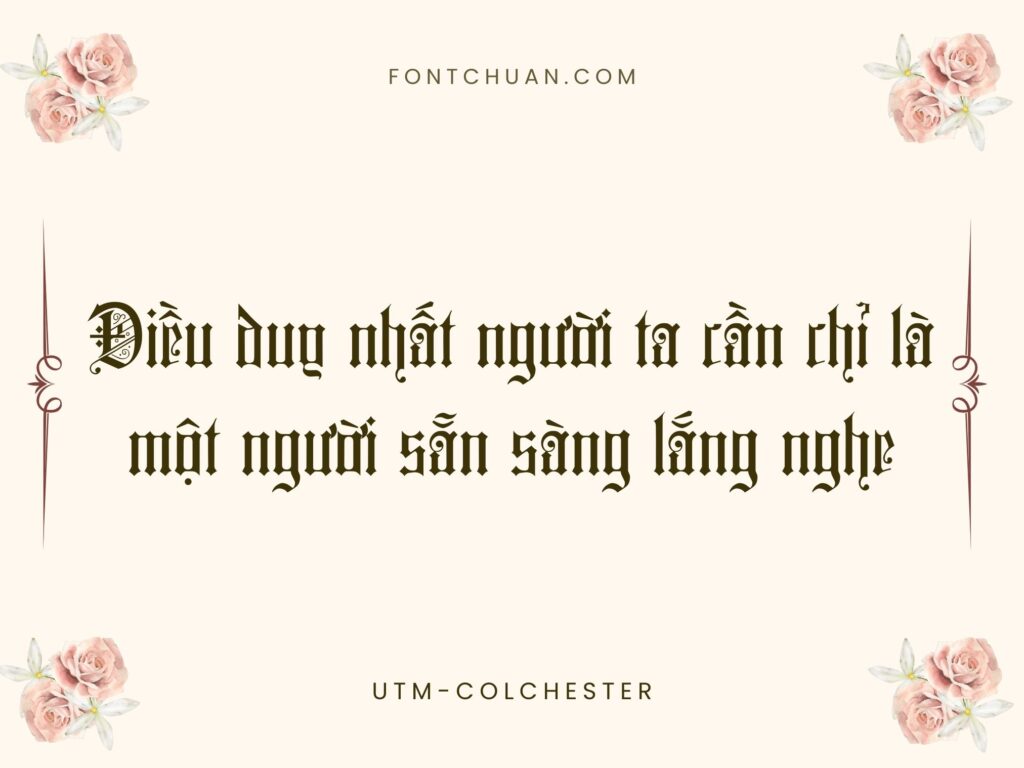
Font UTM Colchester Việt Hóa
UTM Colchester là phiên bản Việt hóa của font chữ Colchester, một Font Vintage mang phong cách thời Trung cổ, được thiết kế bởi Dieter Steffmann. Font này nổi bật với các ký tự có đường nét đậm và góc cạnh, tạo cảm giác cổ điển và huyền bí. Phiên bản Việt hóa đã được thực hiện bởi Đinh Kiên, hỗ trợ đầy đủ tiếng Việt cùng hơn 100 ngôn ngữ khác. Đây là một trong những font được cộng đồng thiết kế sưu tầm và chọn lọc nhằm đáp ứng nhu cầu đa dạng trong thiết kế.
UTM Colchester có cấu trúc chữ với các nét đậm và chi tiết góc cạnh, tạo nên sự nổi bật và thu hút. Font này phù hợp cho các ứng dụng như thiết kế tiêu đề, logo, biển hiệu và các ấn phẩm in ấn yêu cầu sự cổ điển và nghệ thuật. Các ngành nghề như quảng cáo, giáo dục, công nghệ và bất động sản có thể tận dụng UTM Colchester để tạo điểm nhấn độc đáo trong thiết kế.